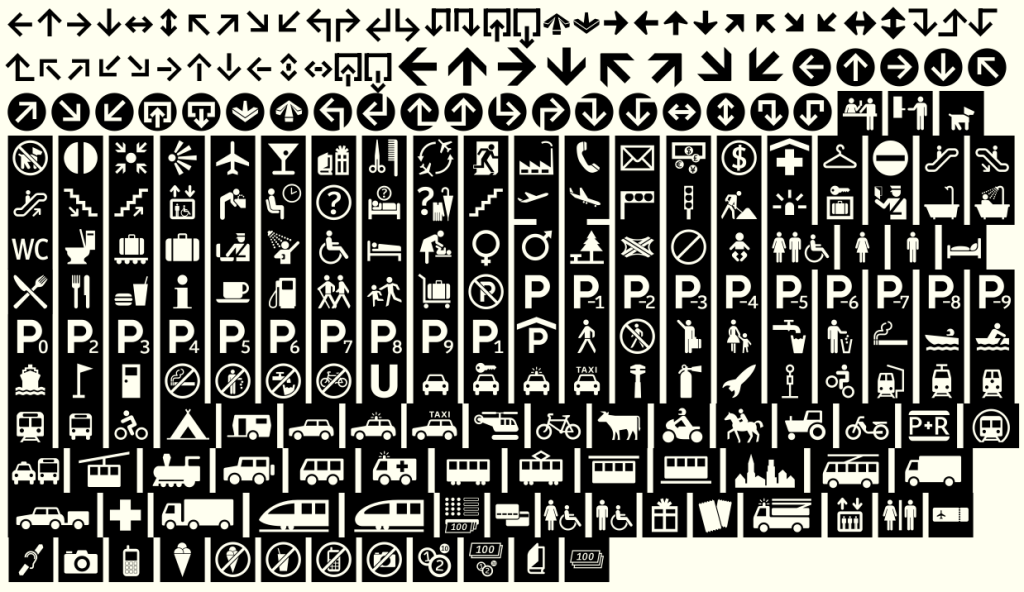
Man sieht aber auch nicht alles in dem Bild.
Sieht man Taxis nicht oder gibt es sie noch nicht? :-)
Wie im richtigen Leben: Wenn man eins braucht, sieht man keins ;-)
Ich verstehe diese ganze rechts-links-Diskussion nicht. Die Ausrichtung des Icons ist doch nicht Sache des Gestalters, sondern des Anwenders, der das doch ohnehin bei Bedarf am Rechner spiegelt — zumindest im Profibereich. Und im Bureaubereich kauft ohnehin niemand einen solchen Font, da wird was aus dem Netz kopiert.
Dinge wie alternative Toilettensymbole für Moslems sind aber durchaus geplant.
Wie hat man sich das denn vorzustellen?
Deshalb haben die Dinge wie Treppen eindeutige Pfeile und verlassen sich natürlich nicht nur auf die Interpretation über die Leserichtung.
Die Pfeile sind eindeutig genug. Jetzt auch noch die Leserichtung einzubeziehen, (also unetrschiedliche Diagonalen für treppauf/treppab) verwirrt logischerweise den, der diese Lesegwohnheit nicht hat.
Kann dann den Effekt ergeben:
Ich verstehe diese ganze rechts-links-Diskussion nicht. Die Ausrichtung des Icons ist doch nicht Sache des Gestalters, sondern des Anwenders, der das doch ohnehin bei Bedarf am Rechner spiegelt — zumindest im Profibereich. …
Mit dem Spiegeln wird aber auch die Durchstreichung gespiegelt, das wäre ja nicht erwünscht …
Nur am Rande bemerkt, falls du daraus ein Schild produzieren lassen möchtest: es wäre nicht notwendig, das auszuschneiden. Die Folien sind opak genug, dass das nicht durchscheint, wenn du die komplette Figur darunter hast. Beim ausgeschnittenen Motiv hast du vielmehr das Problem der Passerungenauigkeit, da das ja von Hand zusammengesetz wird.
Sieht aber nicht schön aus, das übereinander zu kleben. Sieht man schon, wie sich die untere Folie durchdrückt. Also schon ausschneiden und die untere Folie minimal unterschnitten um Blitzer zu vermeiden.
Nein. Bitte keine falschen und praxisfremden Aussagen treffen, kein Beschriftungsunternehmen der Welt arbeitet so. "Minimal unterschnitten" geht bei Folien schon gar nicht.
Mit dem Spiegeln wird aber auch die Durchstreichung gespiegelt, das wäre ja nicht erwünscht …
Da hast Du recht, was diesen Sonderfall angeht.
Nein. Bitte keine falschen und praxisfremden Aussagen treffen, kein Beschriftungsunternehmen der Welt arbeitet so. "Minimal unterschnitten" geht bei Folien schon gar nicht.
Doch, ich mache das so (mal jetzt vorausgesetzt, daß mit »unterschnitten« »überfüllt« gemeint ist). Einfach drüberkleistern halte ich (in Abhängigkeit von der Anwendung) für semiprofessionell.
Nein. Bitte keine falschen und praxisfremden Aussagen treffen, kein Beschriftungsunternehmen der Welt arbeitet so. "Minimal unterschnitten" geht bei Folien schon gar nicht.
UUUps, dann machen wir das seit über 20 Jahren falsch! ;-)
Die Pfeile sind eindeutig genug. Jetzt auch noch die Leserichtung einzubeziehen, (also unetrschiedliche Diagonalen für treppauf/treppab) verwirrt logischerweise den, der diese Lesegwohnheit nicht hat.
Aber das Problem besteht ja so oder so. Entweder sind die Treppensymbole für upstairs und downstairs gleich und es beißt sich also in einem Fall mit der Leserichtung. Oder beide Symbole werden in Leserichtung ausgelegt. Dann stimmt es für Leute mit dieser Leserichtung, aber nicht für jene, mit einer anderen Leserichtung. Eine Variante für alle Fälle gibt mit solchen Symbolen nicht. Welches Szenario wahrscheinlicher ist, müssen die ausführenden Grafikdesigner entscheiden.
In der Praxis dürfte sich ohnehin kaum jemand groß daran stören, da man auf die Symbol intuitiv reagiert und nicht so vergleichend wie hier in der Übersicht. Der explizite Hinweis auf Treppen für nur eine Richtung ist ja ohnehin ein eher seltener Sonderfall.
seh ich einen (wenn wahrscheinlich auch zu venachlässigen) Unterschied.
Wenn ich auf einem Gelände nur immer das eine Treppensymbol sehe ist klar: aha Treppe. Die Richtung gibt der Pfeil vor.
Wenn ich jetzt zwei unterschiedliche Treppensymbole vorfinde erwarte ich logischerweise eine Zusatzinfo.
Wieso auch sonst bräucht es zwei verschiedene. Tja, und diese Zusatzinfo werde ich wohl in der Richtung vermuten. Und schon ist derjenige, der andere Lesegewohnheiten hat, erstmal verwirrt.
Ist die Treppe immer in der gleichen Richtung und letztere durch den Pfeil definiert, herrscht Klarheit.
Deshalb bin ich eben der Meinung, daß du Dir diese Überlegung sparen kannst:
Mal sehen, ob ich das so beibehalte. Die Person auf der Rolltreppe nach unten, die aber in Leserichtung nach oben fährt, ist vielleicht wirklich nicht so optimal.
Zur Leserichtung habe ich mich gestern nochmal mit Mr. Spiekermann beraten. Sie debattieren das auch schon seit Jahrzehnten bei jedem neuen Leitsystem wieder neu. Bislang aber auch ohne die einzig wahre und überall passende Lösung gefunden zu haben.
Was ist mit so einem Kulturzeichen, das auf Sehenswürdigkeiten rechts und links der Autobahn hinweist?
Wohl auch weil auf Vorlagen basierend, die ja auch schon ein paar Jährchen auf dem Buckel haben kommen einige Symbole dann doch etwas nostalgisch (um nicht zu sagen altmodisch) rüber.